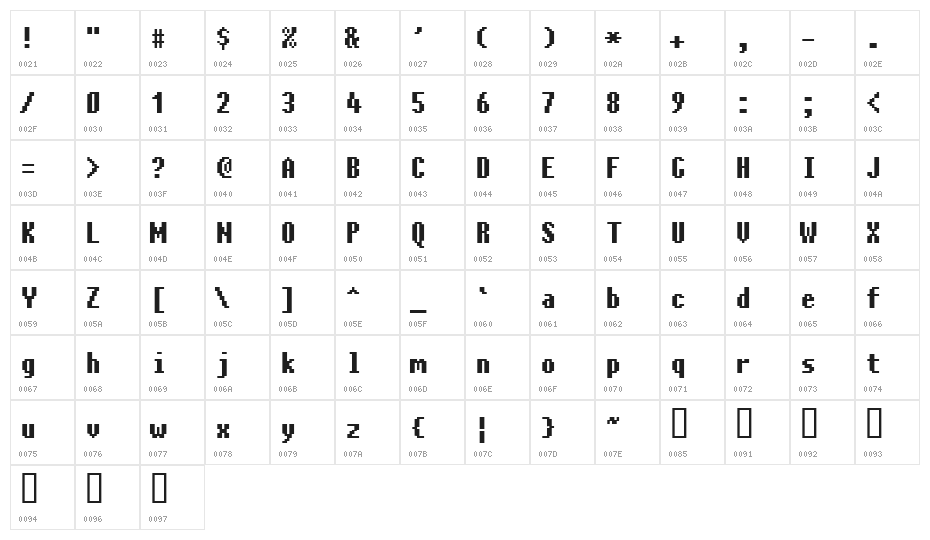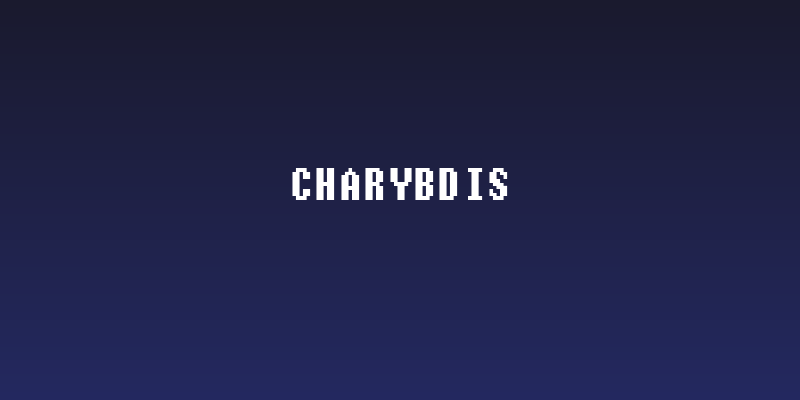
Charybdis Font
| الفئات | Pixel |
| النمط العام | Vintage |
| حالة الاستخدام | Headlines, Logos, Digital Art |
| مشاريع مقترحة | Ideal for retro-themed designs, video game graphics, digital art projects, and any creative work seeking a nostalgic or vintage digital look. |